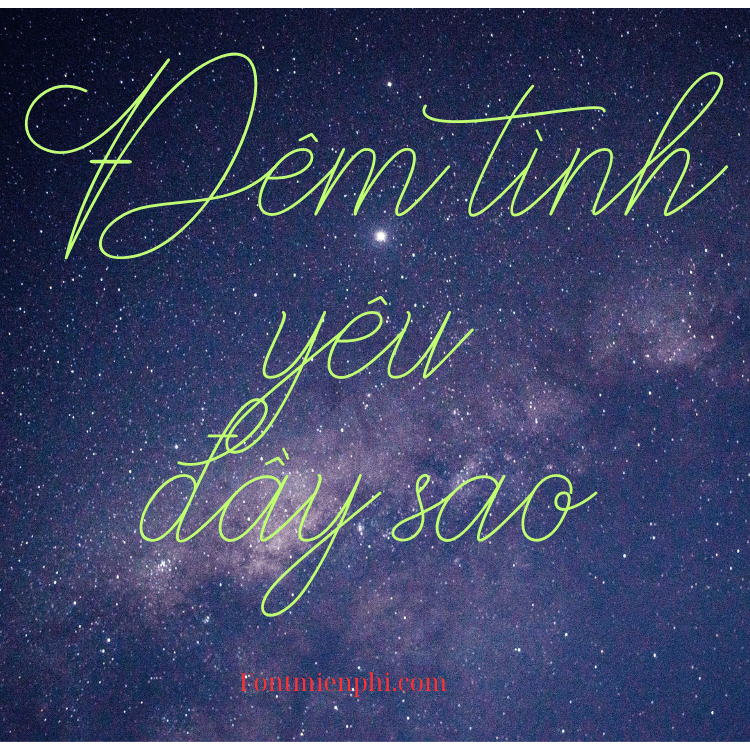
Việt hóa font MTD Abbassy Script cho thiết kế sáng tạo
Giới thiệu bộ Việt hóa font MTD Abbassy Script
Trong thế giới thiết kế đồ họa, việc tìm kiếm một Font Miễn Phí chất lượng và phù hợp với ngôn ngữ tiếng Việt luôn là ưu tiên hàng đầu. Việt hóa font MTD Abbassy Script là một dự án tâm huyết mang đến giải pháp hoàn hảo cho những ai yêu thích phong cách thư pháp hiện đại. Bộ phông chữ này nổi bật với những đường nét uyển chuyển, mềm mại nhưng vẫn giữ được sự mạnh mẽ và sang trọng cần thiết. Nhờ quá trình hiệu chỉnh kỹ lưỡng, các dấu câu tiếng Việt được đặt vị trí chuẩn xác, giúp văn bản trở nên hài hòa và chuyên nghiệp hơn trên mọi ấn phẩm truyền thông.
Đặc điểm nổi bật của Việt hóa font MTD Abbassy Script
Phong cách nghệ thuật ấn tượng
Font MTD Abbassy Script sở hữu cấu trúc chữ viết tay độc đáo với các nét thanh nét đậm đan xen tinh tế. Điều này tạo nên cảm giác gần gũi, tự nhiên như được viết bằng bút mực thật. Khi áp dụng vào các thiết kế như thiệp mời, bìa sách hay logo, font chữ này giúp truyền tải thông điệp một cách cảm xúc và đầy tính nghệ thuật. Khả năng hiển thị tốt trên cả nền tảng kỹ thuật số và in ấn là điểm cộng lớn cho các nhà thiết kế.
Tính ứng dụng linh hoạt trong đời sống
Không chỉ giới hạn trong nghệ thuật, bộ font này còn rất phù hợp cho công việc giảng dạy và học tập. Giáo viên có thể dùng để thiết kế bài giảng sinh động, trong khi học sinh dùng để trang trí báo tường hoặc làm các bài thuyết trình thêm phần bắt mắt. Sự đa dạng trong cách thể hiện giúp người dùng dễ dàng biến hóa phong cách từ cổ điển đến hiện đại mà không gặp bất kỳ rào cản nào về mặt kỹ thuật hay ngôn ngữ.